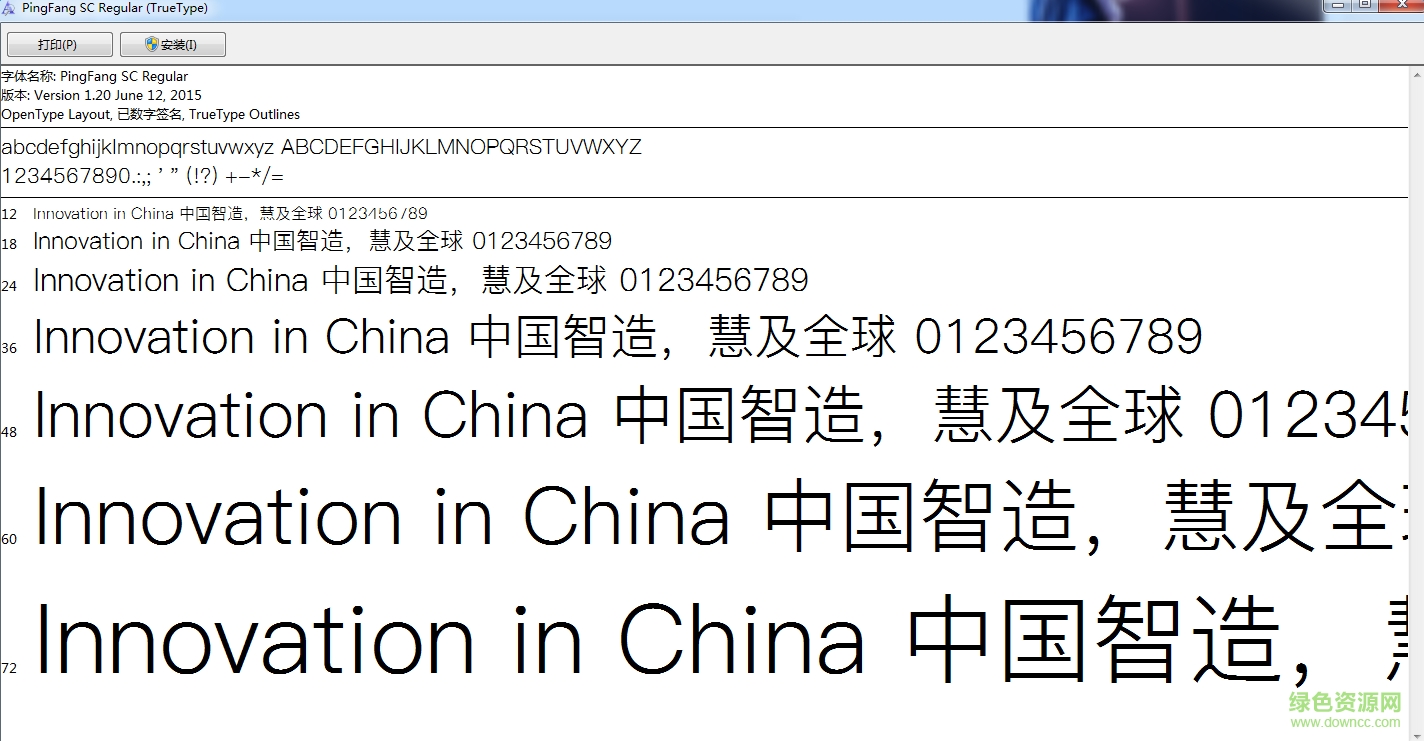
pingfangsclight字體即為蘋方細體字體,字節(jié)纖細端正,常用于圖文印刷、美工創(chuàng)作、名片設計等多種領域,一鍵安裝便捷使用??靵砭G色資源網下載體驗吧!
pingfangsclight是一款非常有特色的電腦字體,共有29951個字符。字符分布范圍:基本拉丁文、拉丁文-1補充、拉丁文擴充-A、拉丁文擴充-B、國際音標擴展、空白修飾字母、組合音標附加符號、希臘文和科普特文、西里爾文、拉丁文擴充增補、希臘文擴充、一般標點符號、上標和下標、貨幣符號、似字母符號、數字形式、箭頭符號、數學運算符號、零雜技術符號、圈型字母數字、制表符、區(qū)塊組件、幾何形狀!